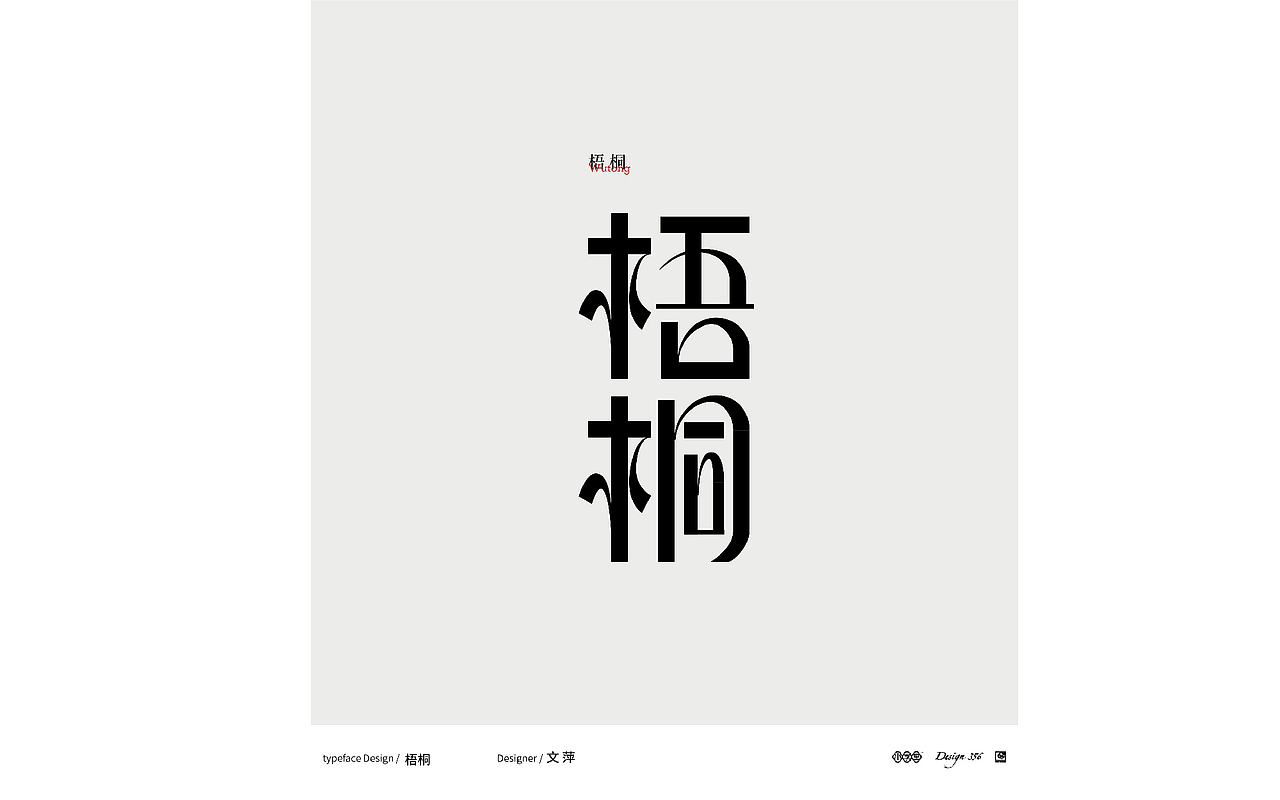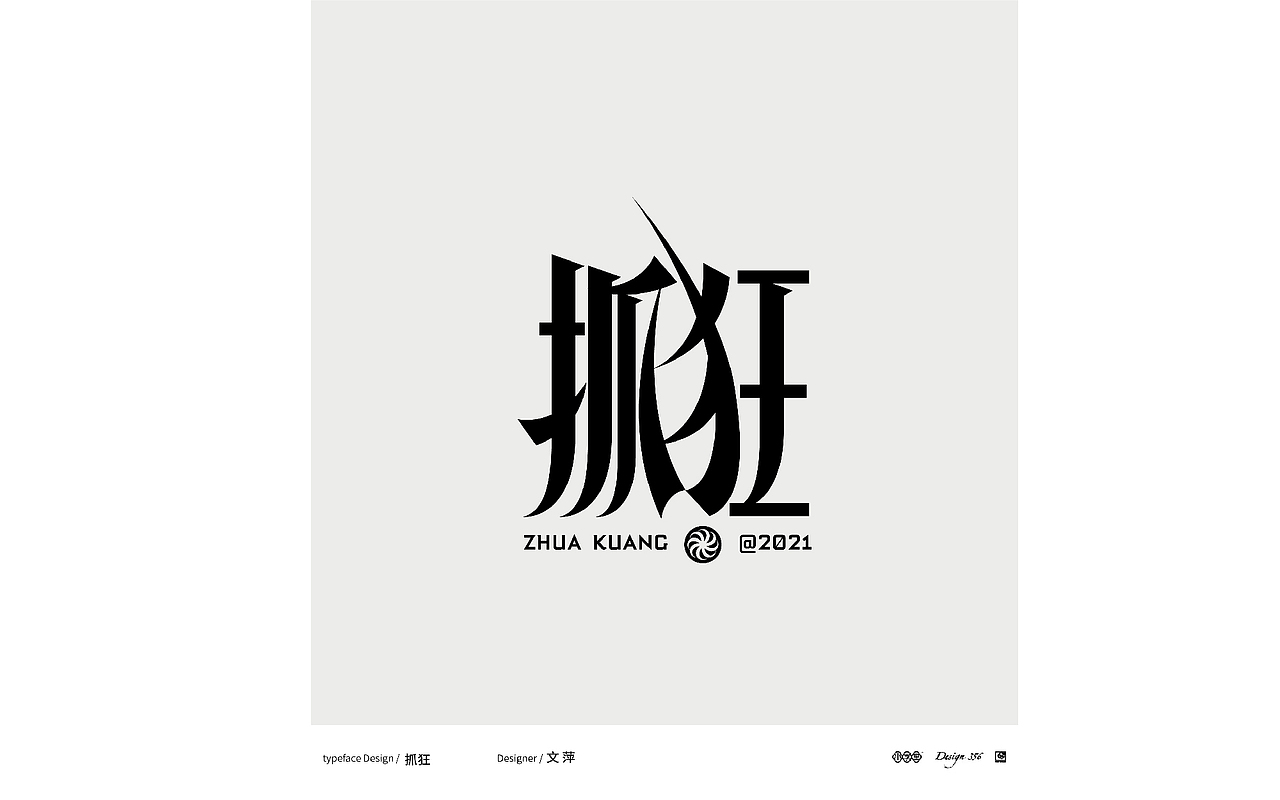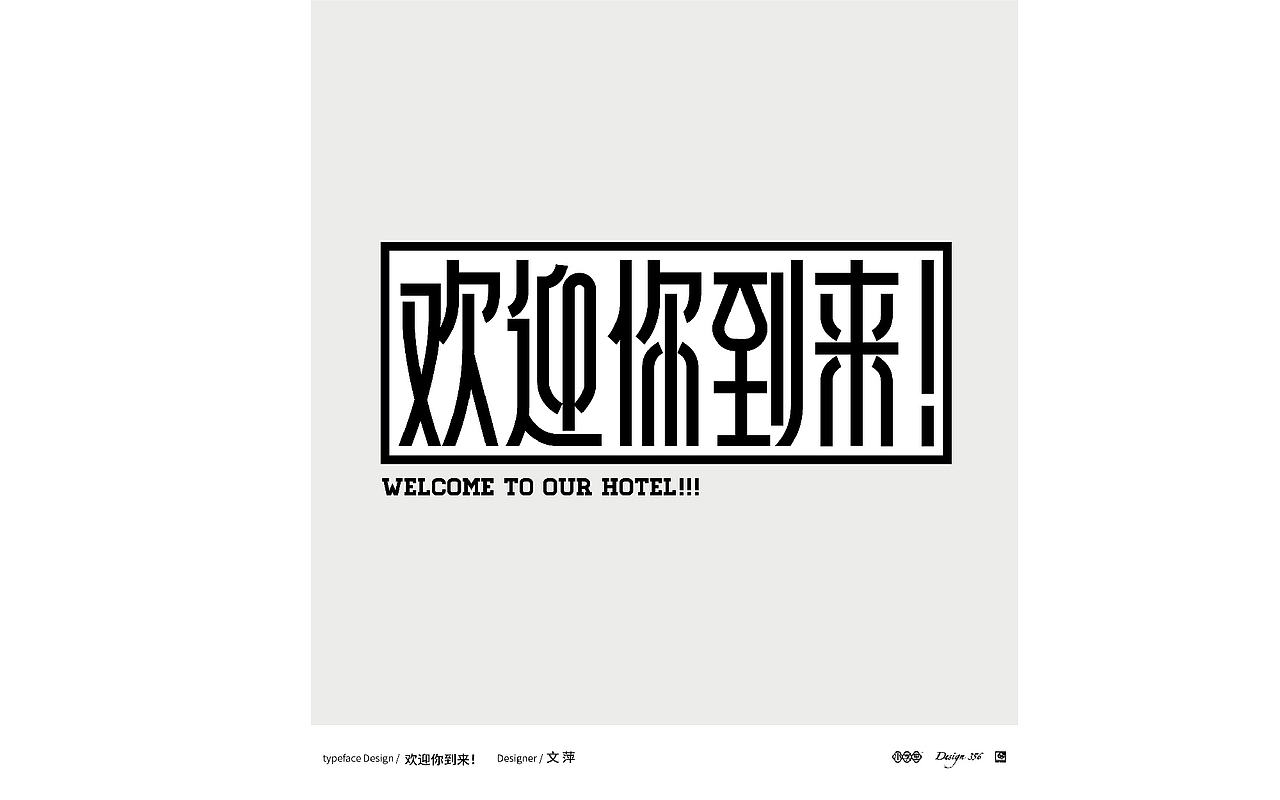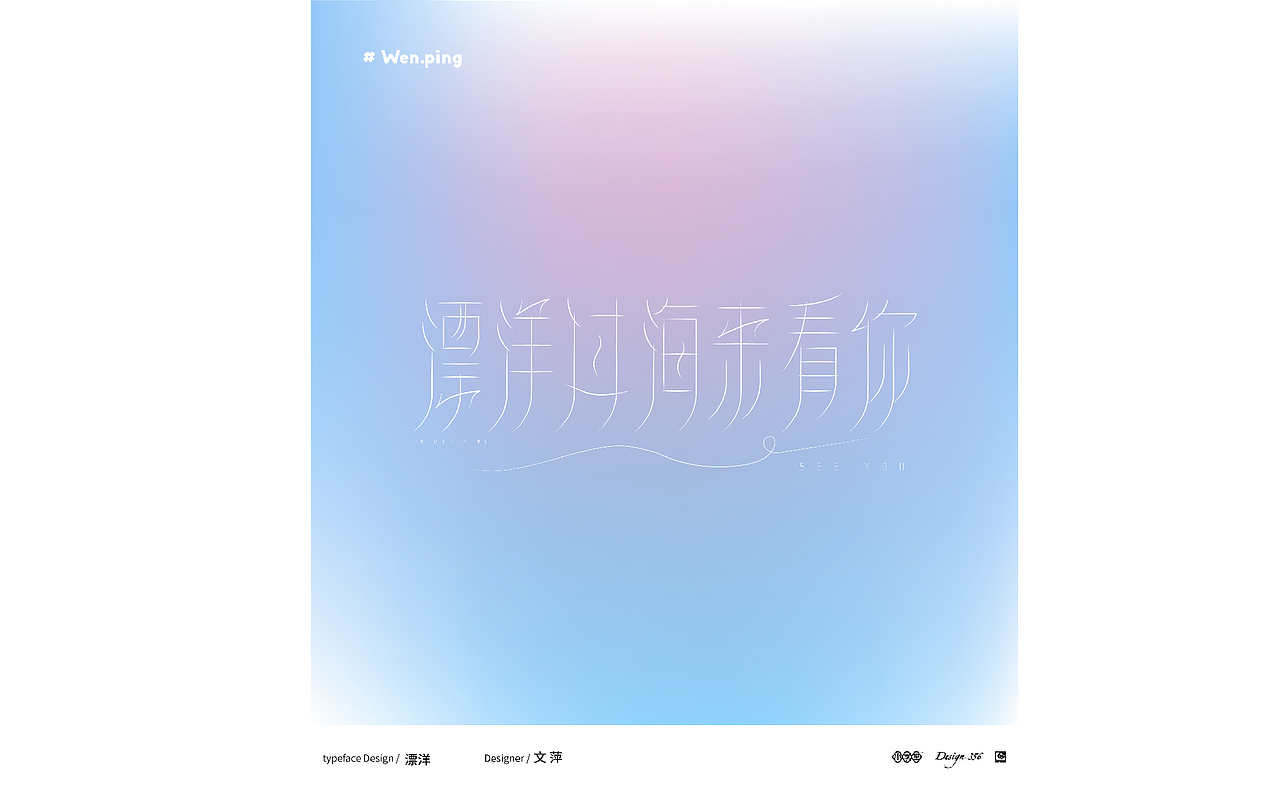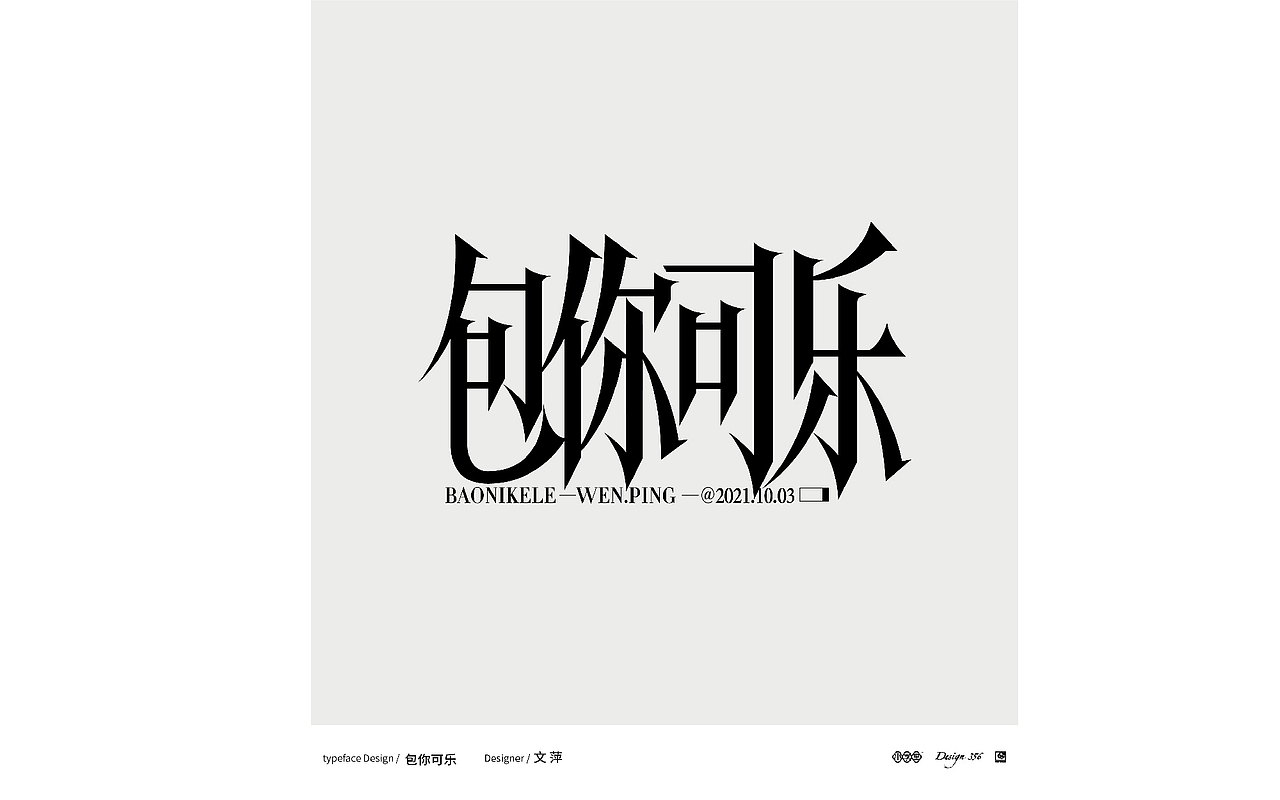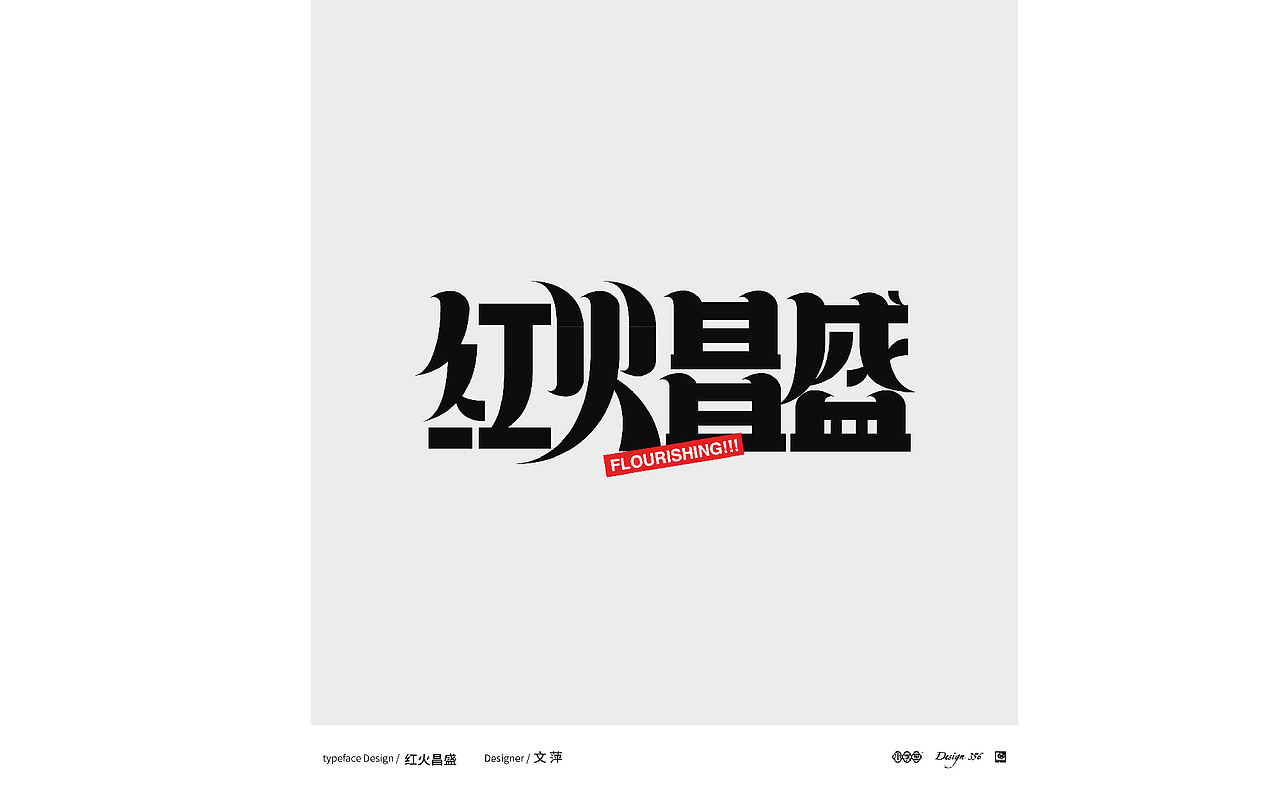
字体设计 | 2021.10.03-10.05
2021.10.03-10.05
及时整理复盘,加油!
每天做点东西
Arrange and re order in time, come on!
参考了些字的笔画特点
走走停停的做着
得之不修,宋体的特点,柔美,笔画间的细节多。
能把折点做好,笔画的顺畅度,在结构稳重的情况在做变化。
虽然也很迷茫
但总要动手做点什么